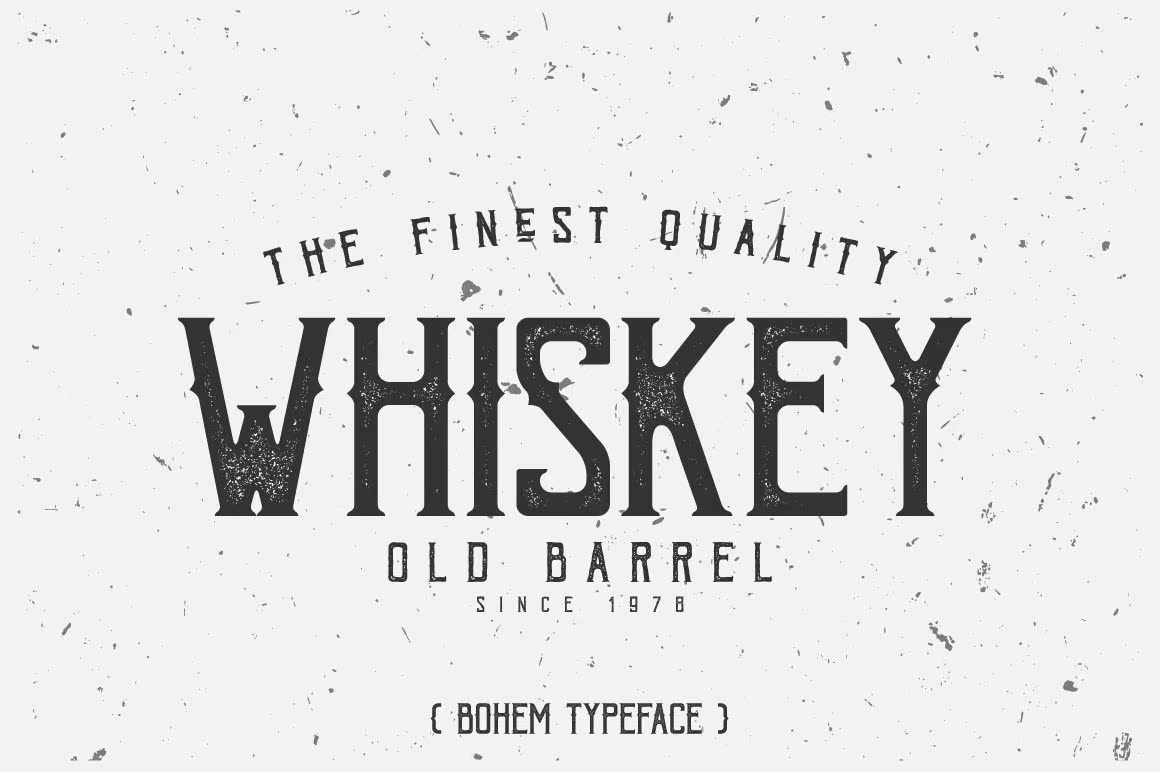
是的,Bohem有5种风格:干净、阴影、压榨、压榨阴影和复古,带有从啤酒厂和酿酒厂生产的葡萄酒特征,非常有助于完成葡萄酒设计。适合并适用于创建葡萄酒设计、品牌、徽标、产品包装、邀请、qoutes、t恤、标签。是的,Bohem有5种风格:干净、阴影、压榨、,按Shadow&Vintage with Vintage从Beer和Breweryit中提取的葡萄酒特征非常有助于进行葡萄酒设计。适用于创建葡萄酒设计、品牌、徽标、产品包装、邀请函、qoutes、t恤、贴标。